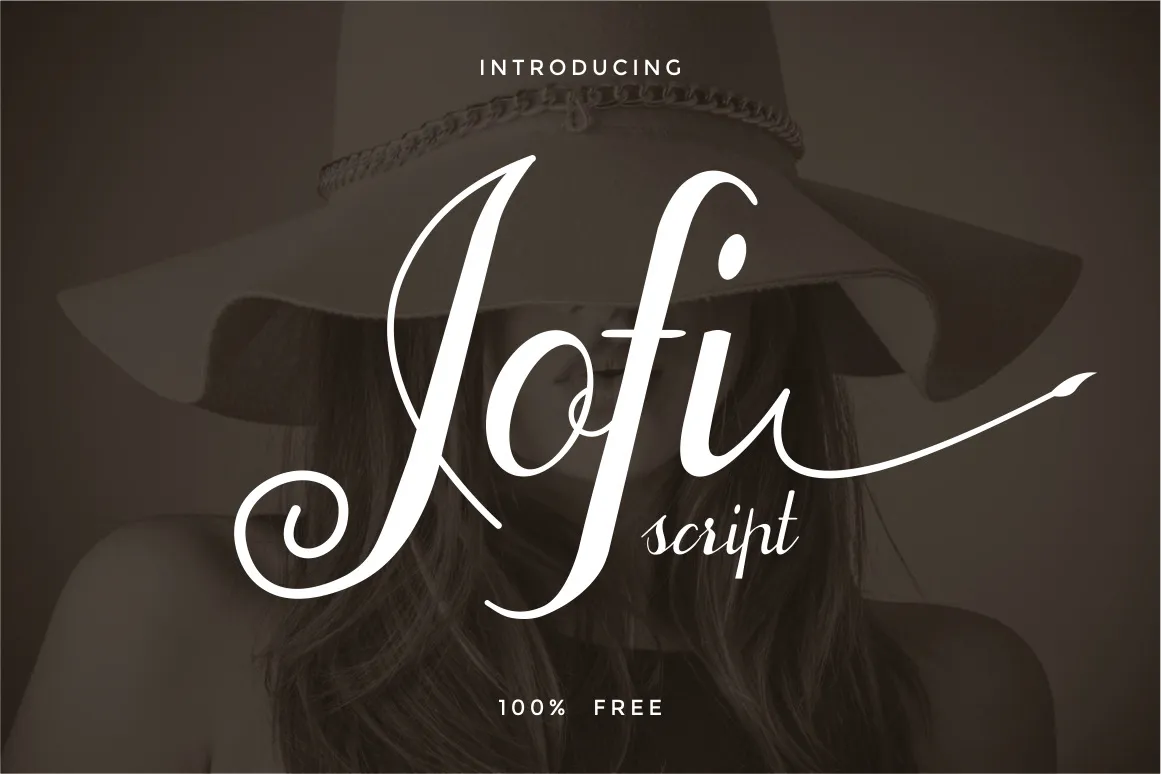
Descubra Jofi Script Font, uma elegante fonte de calligrafia que traz a sofisticação do estilo manufaturado à sua designação digital. Esta fonte foi criada por Hamilton e é perfeita para transformar seus textos em letras estilizadas e modernas. Com Jofi, você pode criar uma identidade visual única, seja para um logotipo ou um site, um layout de revista ou até mesmo convites casuais. Seja qual for o seu projeto, Jofi Script é a escolha certa. Ideal para criação de marca, design de logos, web design, editorial, impressão, cartões de visita, crafts, citações e muito mais. Atrai-emos você com o encanto da elegância do Jofi Font, uma novidade criada por Yunita Ecy para personalizar suas obras de arte digitais de maneira sofisticada e inovadora.